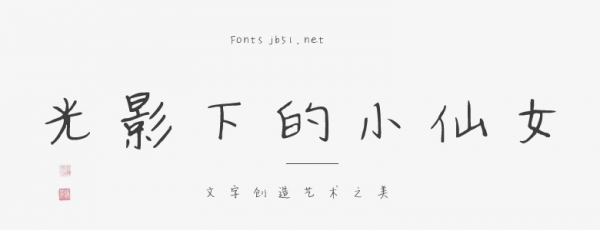
光影下的小仙女,這款字體用筆干脆利落輕重交換,筆畫(huà)多取斜勢(shì)且?guī)в幸欢ǖ幕《?,俏皮可?ài)而又放蕩不羈,個(gè)性感十足極具特色。適用于少兒類(lèi)的書(shū)刊、漫畫(huà)、綜藝影視字幕用字、商業(yè)類(lèi)品牌廣告和產(chǎn)品包裝設(shè)計(jì),以及社交網(wǎng)絡(luò)的個(gè)性化用字。